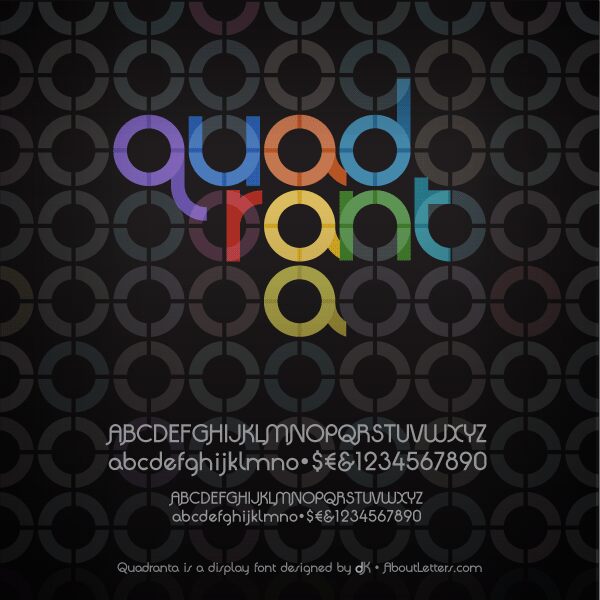
Quadranta Bold di Darim Kim è un carattere tipografico geometrico sans serif da display gratuito, costruito da ampie forme circolari e tratti fermi e uniformi. Le sue rotondità oversize e le giunzioni compatte conferiscono alle lettere un aspetto architettonico e diretto.
Illustrazioni circolari e motivi geometrici ripetitivi possono richiamare queste forme arrotondate in poster e grafica digitale. La forte silhouette si adatta anche al branding tecnologico e alla segnaletica per mostre, dove le lettere possono funzionare quasi come simboli modulari anziché come testo neutro. Il suo territorio d'elezione è il design incentrato sull'architettura, l'arte contemporanea, la musica elettronica o le interfacce futuristiche.
Il design iniziale è iniziato con archi di quadrante, da cui il carattere ha preso il nome.
Quadranta è un font da display.